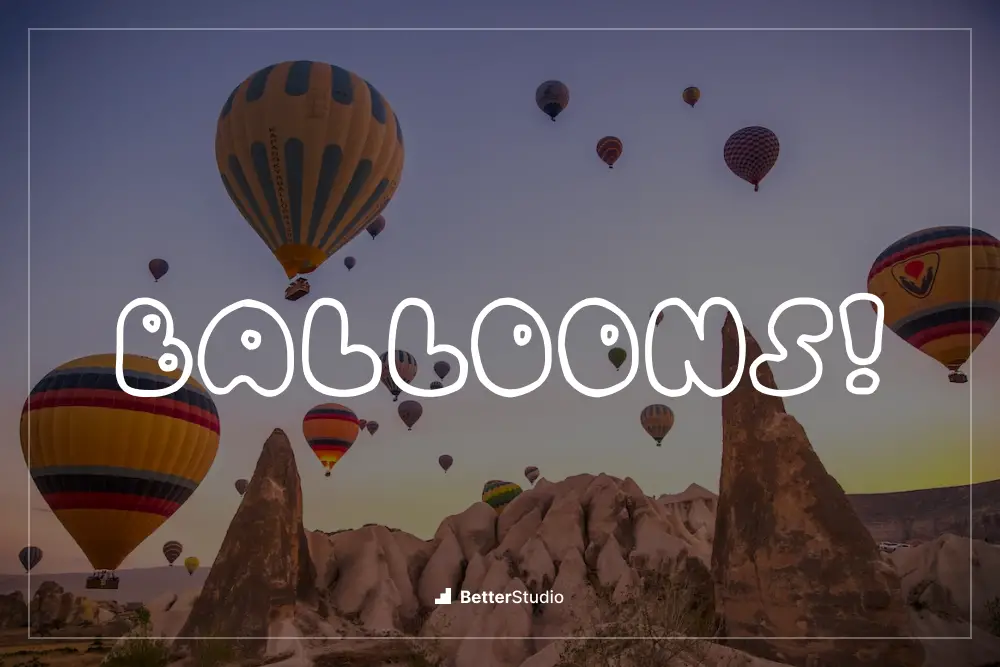
2023 年 17 种最佳气球字体(免费和付费)
已发表: 2023-08-06您是一名平面设计师,希望为您的项目增添一丝奇思妙想和趣味性吗? 别再犹豫了! 在这篇博文中,我们收集了 17 种最好的气球字体,它们一定会将您的设计提升到新的高度。
但您可能想知道,由气球制成的字体如何增强我的项目设计? 好吧,请继续阅读以找出答案!
想象一下一种字体可以轻松地漂浮在页面上,为您的设计增添轻盈感和欢乐感。 这正是您可以使用这些气球字体实现的目标。
无论您是在制作生日邀请函、儿童读物,还是有趣的品牌徽标,这些字体都会为您的项目带来乐趣和奇思妙想。
但不要只相信我们的话。 研究表明,将气球字体等有趣元素融入设计中可以对参与度和用户体验产生积极影响。
事实上,游戏研究所进行的一项研究发现,唤起俏皮感的设计更有可能吸引并保持观众的注意力。
那么,您准备好为您的设计添加一些风格了吗? 加入我们的旅程,我们探索 17 种最好的气球字体,每种字体都有自己独特的风格和魅力。
无论您是经验丰富的设计师还是刚刚起步的设计师,我们精选的清单一定会激发并点燃您的创造力。 准备好利用气球字体的魔力来提升您的设计吧!
最佳高级气球字体
希望通过异想天开的方式提升您的设计项目? 我们精心挑选的 17 种最佳高级气球字体就是您的最佳选择。
这些独特的字体保证能为任何设计增添有趣且引人注目的元素。 因此,继续探索完美的字体,将您的项目提升到新的高度!
气球梦
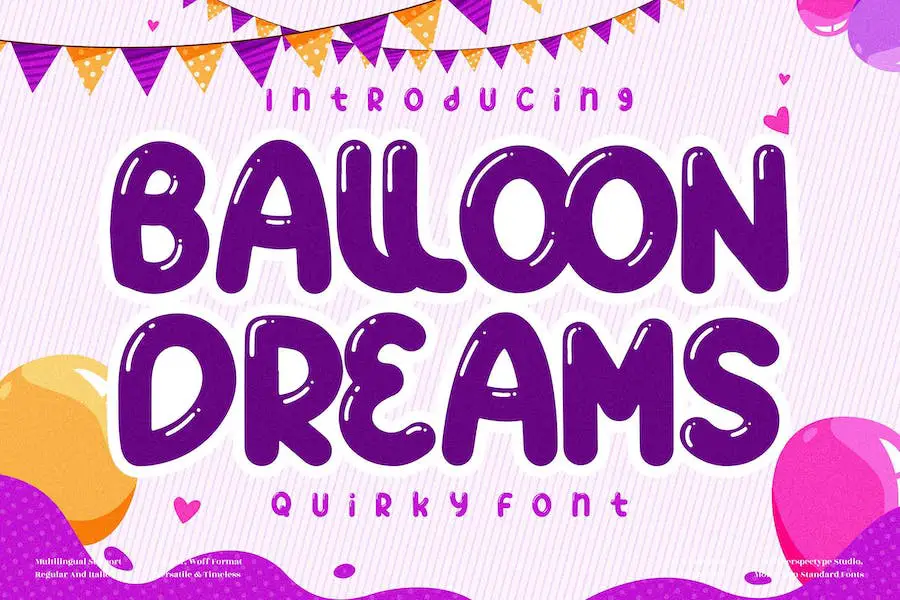
Balloon Dream 是一款出色的字体,非常适合为您的设计项目添加俏皮的感觉。 无论您是要创建海报、社交媒体帖子还是个人项目,这种字体一定会脱颖而出。 凭借其活泼有趣的设计,它非常适合为您的创作增添一丝奇思妙想。
Balloon Dream 的突出特点之一是它的多功能性。 它可用于多种用途,使其成为任何设计师工具包的宝贵补充。 无论您想要可爱可爱的外观还是轻松有趣的氛围,这款字体都能满足您的需求。
这种字体的圆形和光滑的边缘赋予它独特和引人注目的吸引力。 它是需要魅力和个性的项目的完美选择。
Balloon Dream 凭借其易于阅读的字母和俏皮的风格,确保您的信息能够吸引注意力并产生影响。
气球
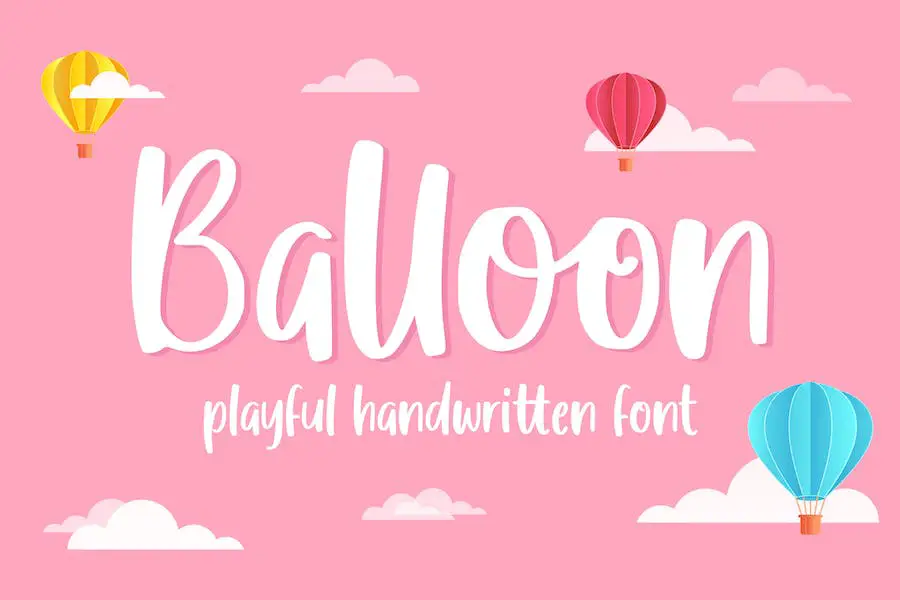
Balloon 是一种令人愉悦且有趣的显示字体,非常适合为您的设计项目增添一丝欢乐。 凭借其可爱和异想天开的风格,它一定会让您的创意脱颖而出。
将这种美丽的字体融入您的设计中,看着它们以欢快而充满活力的能量变得栩栩如生。 无论您是在制作生日请柬、派对横幅还是任何其他需要节日和有趣氛围的设计,气球都是完美的选择。
那么为什么不添加一些生日气球字体到您的收藏中并让您的创造力飙升呢?
气球
对于想要将项目提升到新高度的图形设计师来说,“Air Balloon”字体是必备的。 这种字体以其迷人、俏皮和异想天开的风格,非常适合为任何设计增添一丝乐趣和兴奋。 另外,它是手绘的,给人一种独特而真实的感觉。
“气球”字体的美妙之处在于它能够将您的观众带入一个奇思妙想和欢乐的世界。
想象一下儿童读物、生日聚会邀请函或任何需要轻松愉快的设计项目的可能性。 这种字体真正捕捉到了乐趣和冒险的精神。
那为什么还要等呢? 让您的设计“Up,Up and Awayyyyy!” 带有“气球”字体。 让它释放您的创造力,让您的项目腾飞。 相信我,一旦您看到它为您的设计带来的魔力,您就会想知道如果没有它您将如何生活。
赫利乌姆
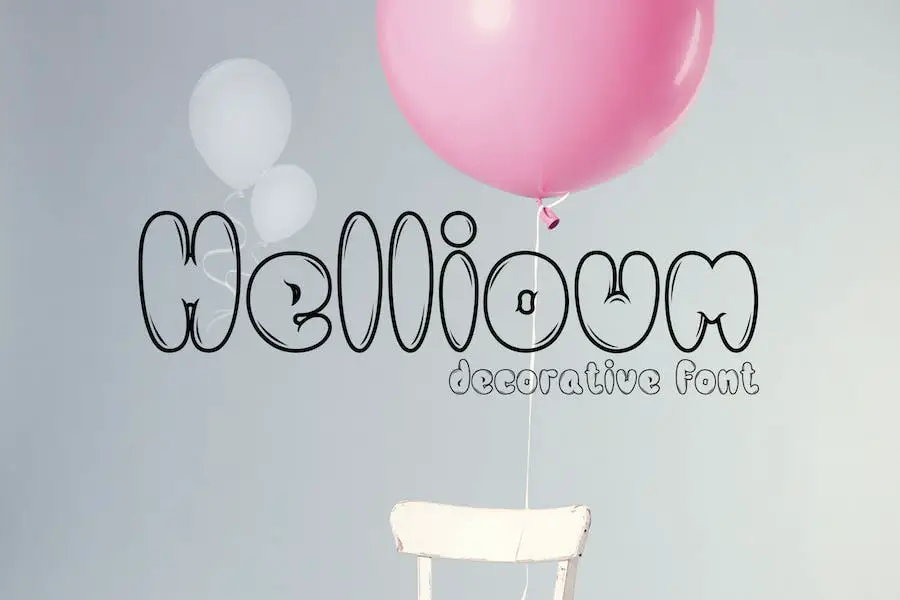
Hellioum 是一种独特的字体,其灵感来自于咖啡馆中发现的海报设计。 它是手工精心制作的,为任何设计项目带来自然、手工的感觉。
Hellioum 字体非常适合希望通过异想天开和俏皮氛围来增强其项目的图形设计师。 其气球般的形状给人一种节日和庆祝的感觉,使其成为生日邀请函、派对装饰和其他欢乐场合的绝佳选择。
Hellioum 的突出特点之一是它能够让人产生铝箔气球的感觉。 每个字母精心设计的曲线和轮廓模仿了这些节日装饰品光滑闪亮的表面。
气球颜色字体
Balloons Color Font 是一种奇妙的字体,可为您的图形设计项目增添俏皮和欢快的感觉。 这种独特的字体采用双色或 SVG Opentype 格式,这意味着它可以在 Photoshop CC 2017+、Illustrator CC 2018 和某些 Mac 应用程序中完美运行。
使用气球颜色字体,您可以轻松创建引人注目的设计,其中融入充满活力的气球状元素。 该字体的双色功能使您可以为文本添加深度和尺寸,使其更具视觉吸引力。
无论您是在制作数字插图、品牌项目还是聚会邀请函,这种字体都一定会提升您的设计并吸引观众的注意力。
气球
气球是一种由棒棒糖手绘创建的令人愉快的字体。 凭借其圆润可爱的设计,它为任何项目增添了一丝奇思妙想。 气泡气球字体非常适合希望通过有趣且俏皮的字体来增强其设计的图形设计师。
Balloon 字体还提供了一系列风格替代方案,包括不同的字母形式和连字。 这使您可以试验和定制您的设计,为您提供更多的创作自由。
无论您是想强调某些字母还是创建独特的外观,气球字体都能满足您的需求。
蓟气球
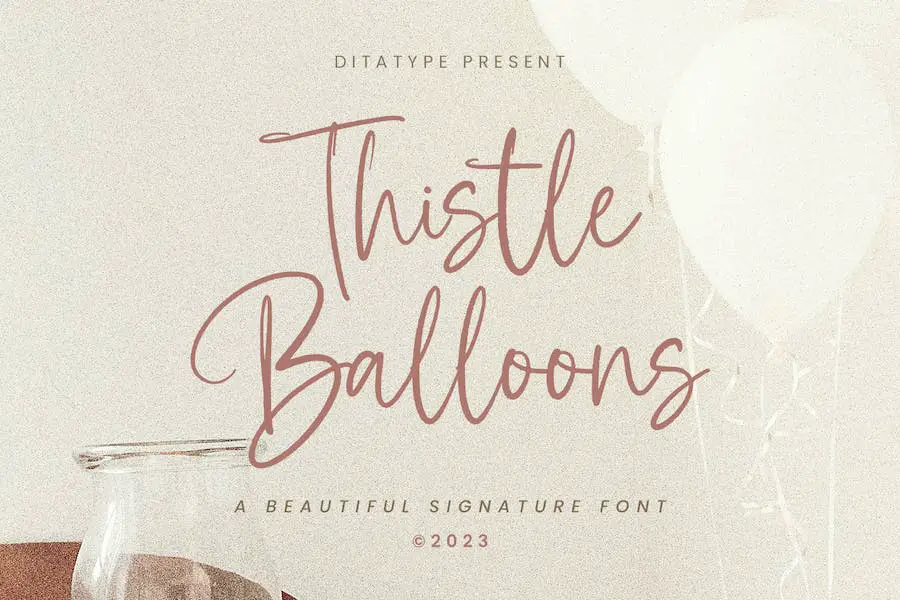
对于那些希望为自己的设计添加自然、休闲和个人风格的人来说,Thistle Balloons 是完美的脚本字体。 这些字母精美地连接在一起,营造出一种团结和连续的感觉,给您的项目带来独特而真实的感觉。
凭借其低字母对比度,这种字体散发出休闲和友好的氛围,非常适合营造温暖而诱人的显示效果。 字母高度的变化为字体增添了有趣和动态的元素,进一步增强了其自然和个人的细微差别。
对于较大的文本尺寸,建议使用 Thistle Balloons,以充分欣赏其出色的功能。 您一定会喜欢这种字体为您的设计带来的魅力和个性。
轰炸机气球
Bomber Balloon 是一款有趣的字体,非常适合各种设计项目。 无论您需要徽标、引言、海报、有趣的字体还是完美的服装字体,这款字体都能满足您的需求。
凭借其有趣和充满活力的风格,它为任何设计增添了独特的触感。 因此,如果您是一名图形设计师,正在寻找完美的气球字体来增强您的项目,那么 Bomber Balloon 就是您的最佳选择。
它用途广泛、引人注目,一定能将您的设计提升到一个新的水平。 尝试一下,看看它给您的创作带来的魔力。
太阳黑子
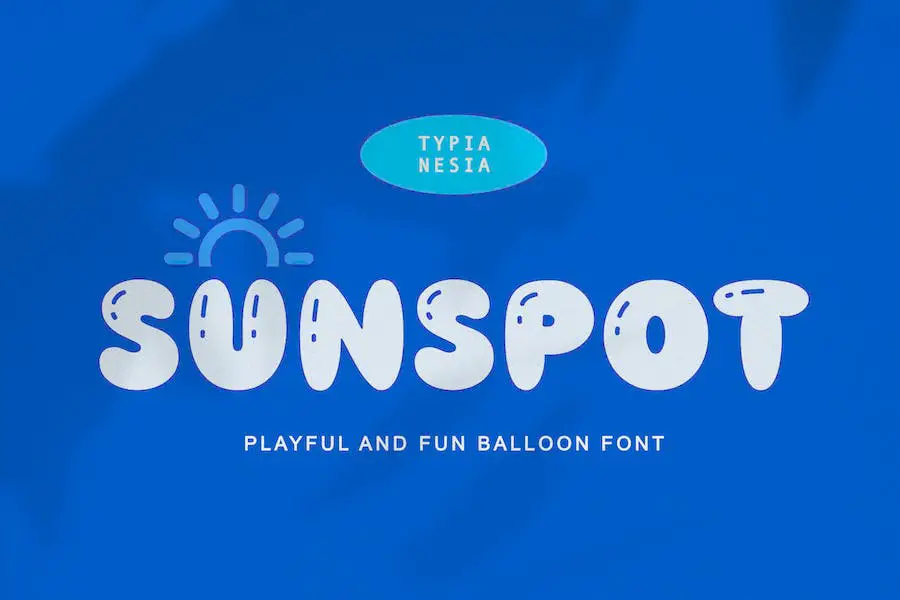
Sunspot 是一种气泡气球字体,非常适合各种设计目的。 无论您是要创建儿童游戏徽标、零食包装,还是幼儿园的品牌推广,它都可以轻松增强您的项目。
这种字体也非常适合食品和饮料包装以及儿童和儿童玩具品牌。 凭借其俏皮有趣的设计,Sunspot 是广告设计、生日派对、卡通动画和玩具品牌的绝佳选择。
您还可以将其用于海报引言、儿童读物或封面标题以及您可能有的任何其他设计需求。 它的多功能性和魅力使其成为想要提升项目水平的平面设计师的必备工具。
爱你
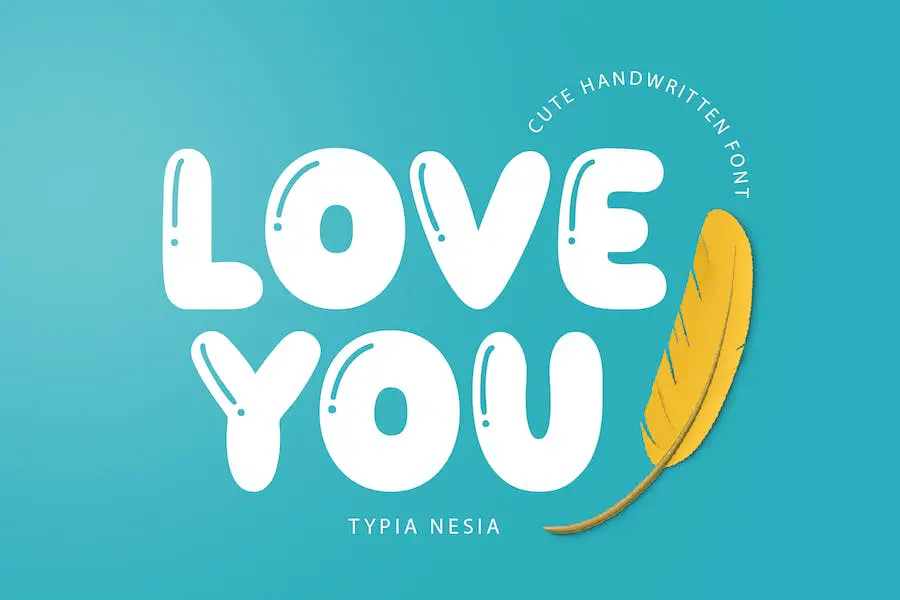
Love You 是一款精美的气球字体,非常适合各种设计项目。 无论您是为儿童游戏创建徽标、为零食产品设计包装,还是制作生日聚会邀请函,这款字体都能满足您的需求。
它俏皮又有趣,使其成为儿童设计的绝佳选择。 凭借其现代风格和引人注目的吸引力,Love You 将为任何项目增添一抹魅力。
从海报和书籍封面到网站和卡片,这种字体用途广泛,可满足您所有的手写需求。 尝试一下,看看您的设计变成现实!
比尔德万斯
Beardvans 是一种现代的呕吐气泡和气球涂鸦字体,体现了街头和城市文化。
凭借其艺术设计,它是各种项目的完美选择,包括标志品牌、编辑设计、体育设计、游戏和游戏行业、音乐封面和海报、网站设计、现代广告设计、现代海报引言、书籍和杂志封面标题、和特别活动。
这种气泡气球字体为您的设计增添了俏皮和充满活力的感觉,使它们在视觉上有吸引力且引人注目。 其独特的风格捕捉了街头艺术的精髓,让您能够创造出脱颖而出的设计。
无论您是在为运动队、音乐活动还是前卫品牌开展项目,Beardvans 字体都能让您的设计栩栩如生。
其大胆而充满活力的字体营造出一种活力和兴奋感,使其成为需要城市和现代外观的项目的完美选择。
易黑客
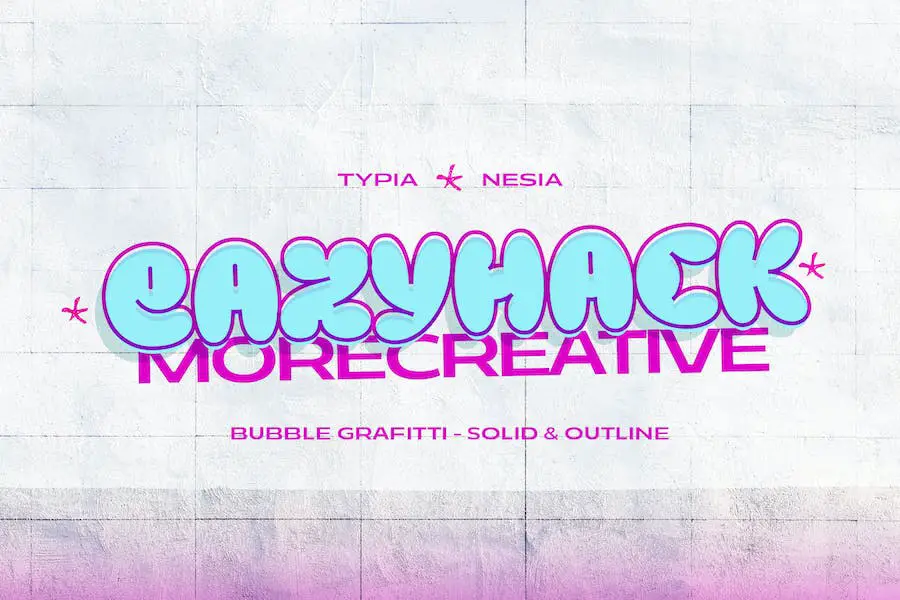
Eazyhack 是一种现代的呕吐气泡/气球涂鸦字体,体现了街头和城市文化,具有儿童友好和有趣的游戏般的吸引力。
该字体是各种项目的理想选择,包括徽标品牌、编辑设计、体育设计、游戏或游戏行业项目、音乐封面和海报、网站设计、现代广告、海报引用、书籍或杂志封面标题,以及特别活动。
凭借其大胆而引人注目的设计,Eazyhack 为任何设计项目增添了俏皮的气息。 活泼的字母营造出一种兴奋和活力的感觉,使其成为需要吸引注意力并在人群中脱颖而出的项目的完美选择。
无论您是为儿童品牌设计徽标,还是为特殊活动制作引人注目的海报,这种字体都会为您的工作增添一丝乐趣和创造力。
Eazyhack 的一大优点是它与不同设计软件和平台的兼容性。
无论您是在 Adobe Illustrator、Photoshop 还是 InDesign 中工作,此字体都将无缝集成到您的工作流程中,从而轻松融入您的设计项目中。
最好的免费气球字体
希望为您的设计增添俏皮感? 我们精选的最佳免费气球字体就是您的最佳选择! 这些异想天开的字体一定会给您的项目带来乐趣和魅力。 所以,继续吧,看看并发现完美的字体,将您的设计提升到新的高度!
气球
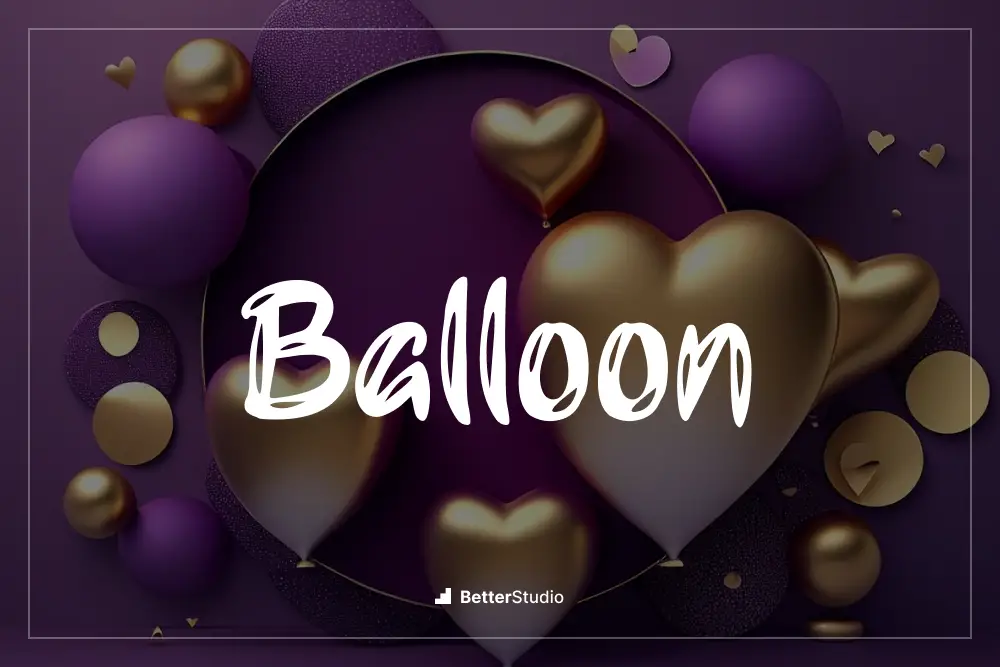
Bandofol Studio 的 Balloon 是一个出色的字体集合,专为希望通过一丝乐趣和俏皮来增强其项目的图形设计师而设计。
这些气球字体非常适合创造引人注目的设计,特别是生日庆祝活动和其他节日场合。 使用 Balloon,您可以轻松为您的设计添加异想天开和欢快的氛围。
Balloon 最好的事情之一是它是专门为与流行的图形设计平台 Canva 一起使用而设计的。 这意味着您可以直接在 Canva 中轻松访问和使用这些字体,无需任何麻烦或额外的步骤。
与 Canva 的无缝集成可确保设计流程顺利高效,为您节省宝贵的时间和精力。
巴隆库
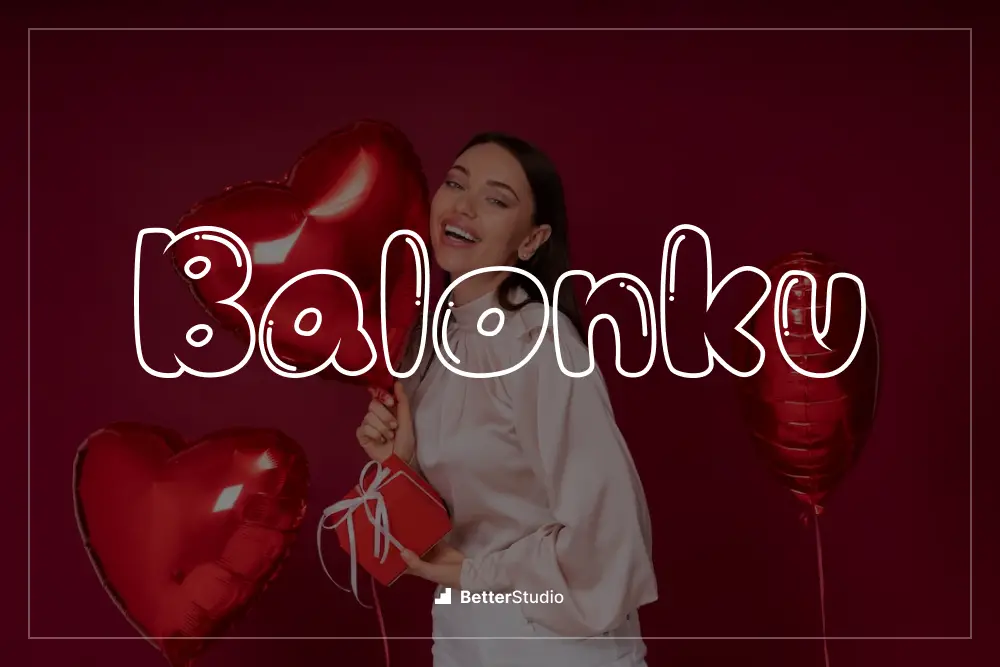
Balonku 是每个平面设计师在他们的项目中都应该考虑的字体。 它非常适合为任何设计增添有趣和俏皮的感觉,尤其是那些与生日或庆祝活动相关的设计。
Balonku 以其气泡状的外观吸引注意力,并为任何文本增添欢快的氛围。
字体的属性使其真正与众不同。 其圆润流畅的字体就像充气的气球,给人一种喜悦和幸福的感觉。 每个角色都有独特的形状,模仿气球的曲线和轮廓,使其立即可识别且引人注目。
Balonku 以其俏皮和异想天开的风格,一定会让任何设计脱颖而出。
Balonku 与其他气球字体的区别在于它对细节的关注。 每个字母都经过精心制作,以确保即使尺寸较小,也能保持气球般的形状。 这意味着您可以在各种设计元素中使用该字体,而不会影响其易读性。
还建议在正文中谨慎使用气球字体,而将重点放在标题、标题或装饰元素上。
使用气球字体可以为您的设计添加有趣和充满活力的元素,使它们更具视觉吸引力和吸引力。
它们非常适合制作邀请函、贺卡、横幅和其他节日材料。 气球字体可以帮助您捕捉活动的欢乐和庆祝气氛。
结论
为了结束我们关于 17 种最佳气球字体的文章,我们探索了各种独特且引人注目的选项,可以将您的图形设计项目提升到一个新的水平。
我们讨论了选择正确字体来增强项目设计的重要性,以及这些气球风格的字体如何为您的创作增添俏皮感。